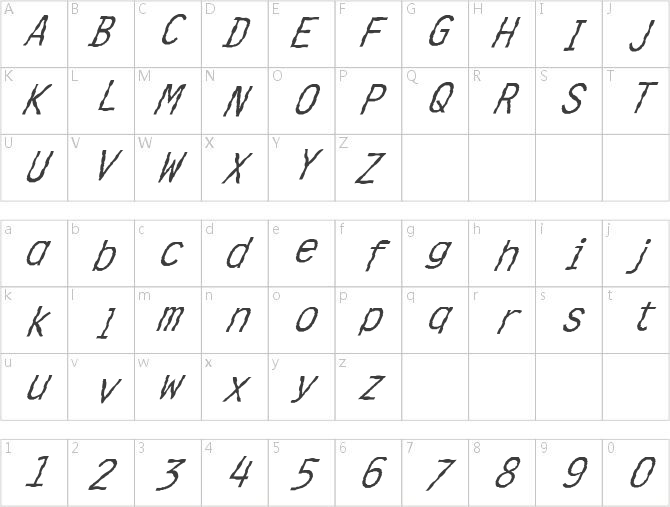
FZ DIGITAL 4 WAVEY ITALIC
FZ DIGITAL 4 WAVEY ITALIC介绍
FZ DIGITAL 4 WAVEY ITALIC字体字库是一款让人赏心悦目、百看不厌的英文字体,适合各类广告和产品包装设计应用,字体大小0.07MB,格式为ttf字体,上传用户是多喝烫水,作者/版权方为未知